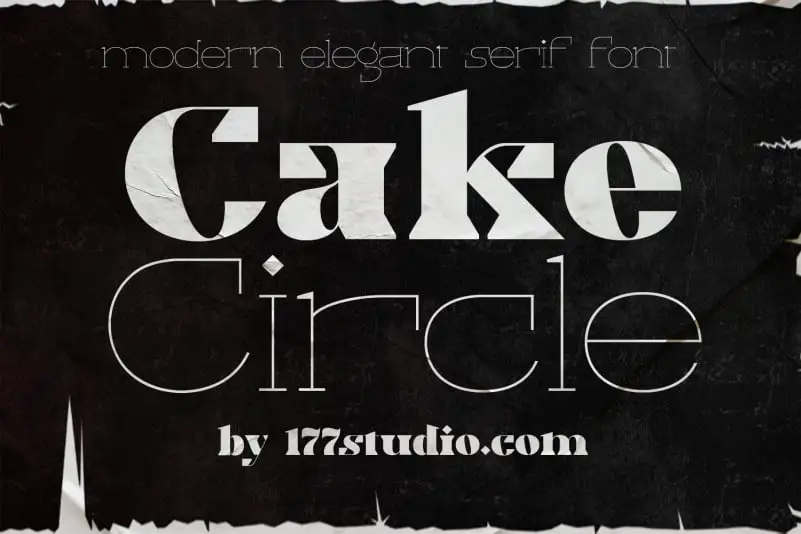
Cake Circle Font – Download Grátis
A Cake Circle Font é uma elegante fonte serif moderna inspirada por transições contemporâneas do design tipográfico. Este famoso conjunto de caracteres possui um alto x-height, proporções modernas e acusadas serifas, com traços extremamente contrastados que desempenham o papel de estresse vertical. Perfeito para uma variedade de projetos, ela é perfeita para aplicar em revistas fashion, identidade visual, marca personalizada, cartões de aniversário de casamento, invocações e até mesmo para assinaturas no blog ou para usar nos títulos dos posts, carteirinha publicitária, banner publicitário, cartão postais, capa de livros e para o design em tela. A Cake Circle Font é um recurso fonte ideal para designers e profissionais do design gráfico.